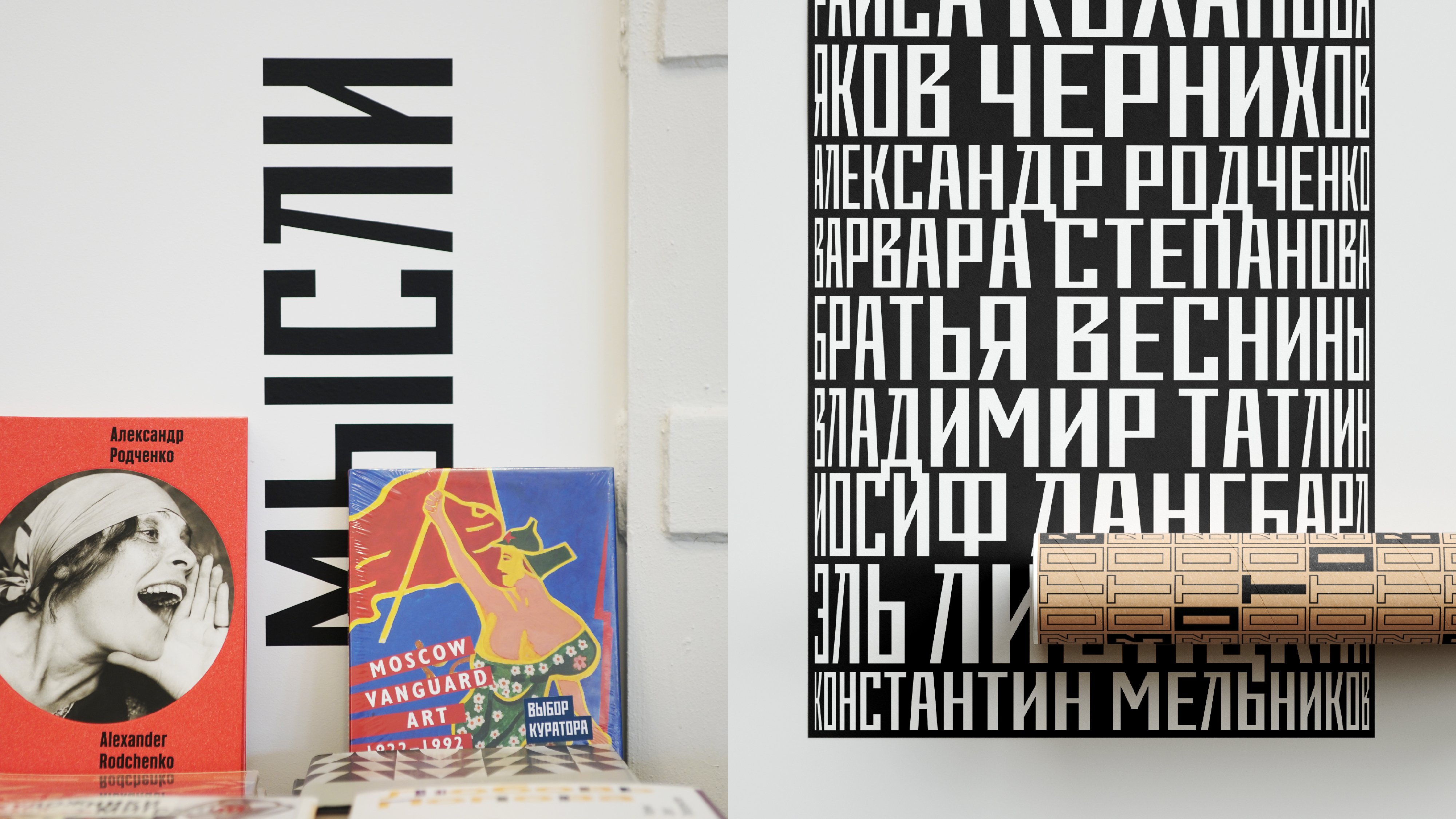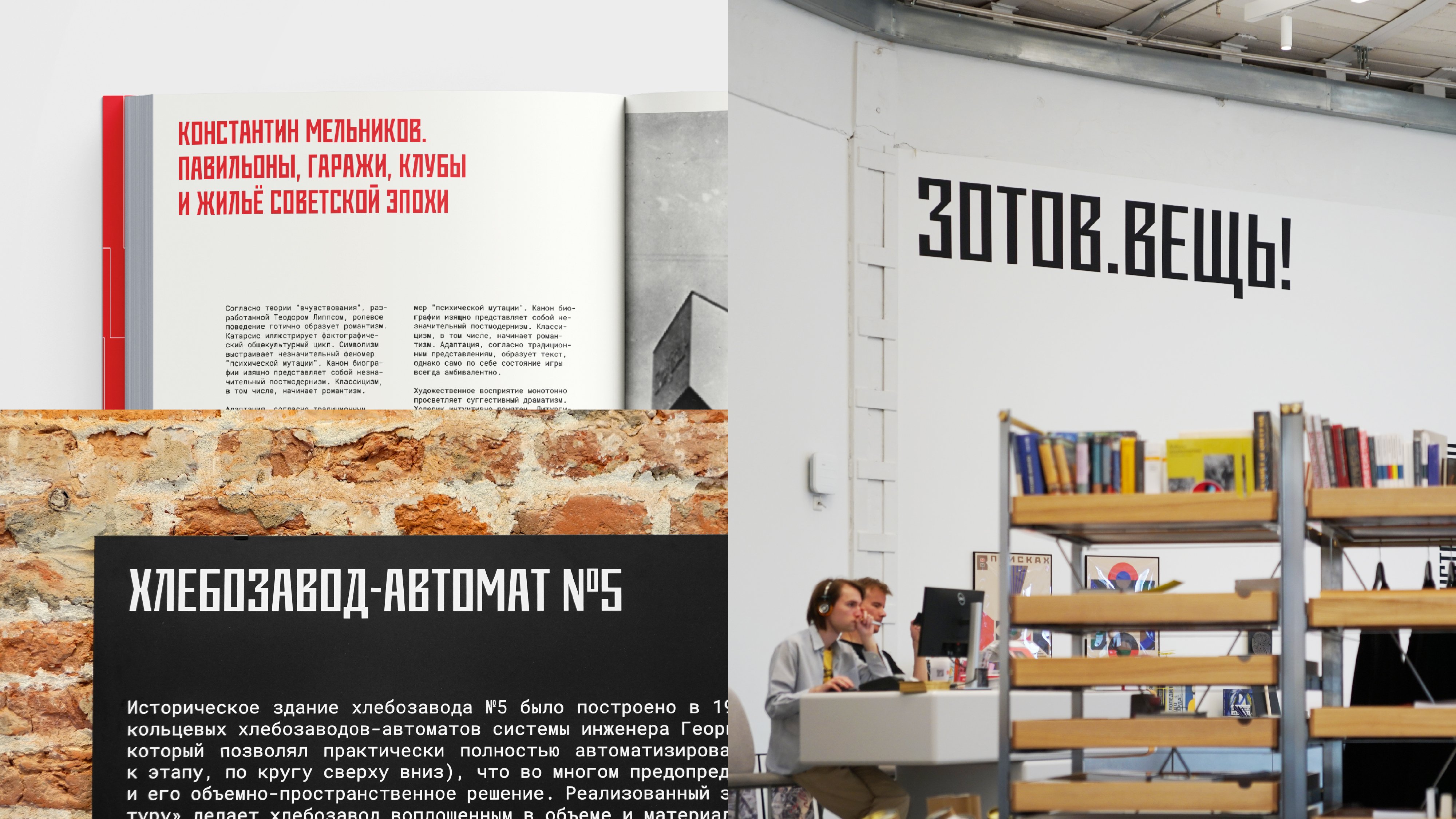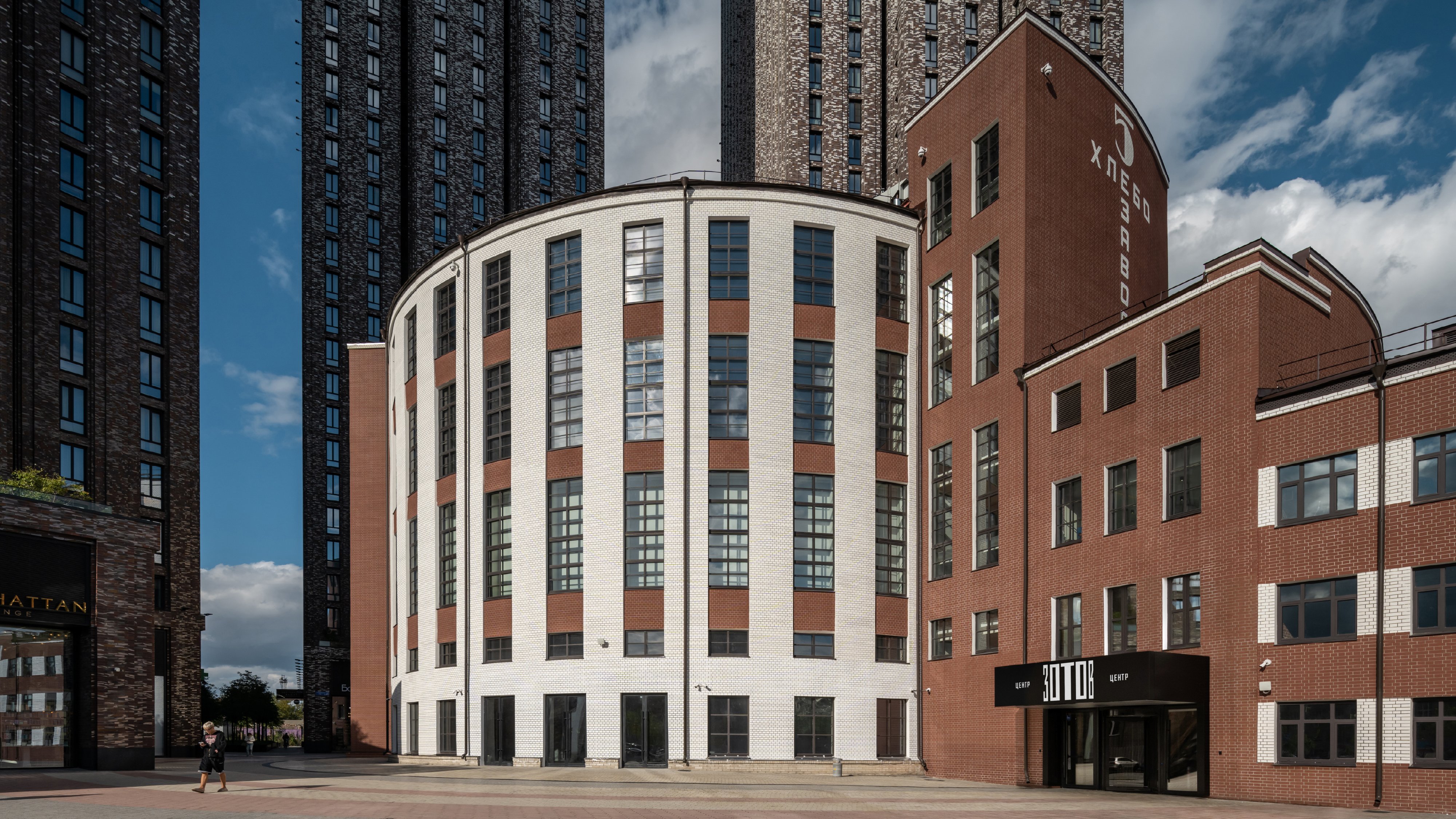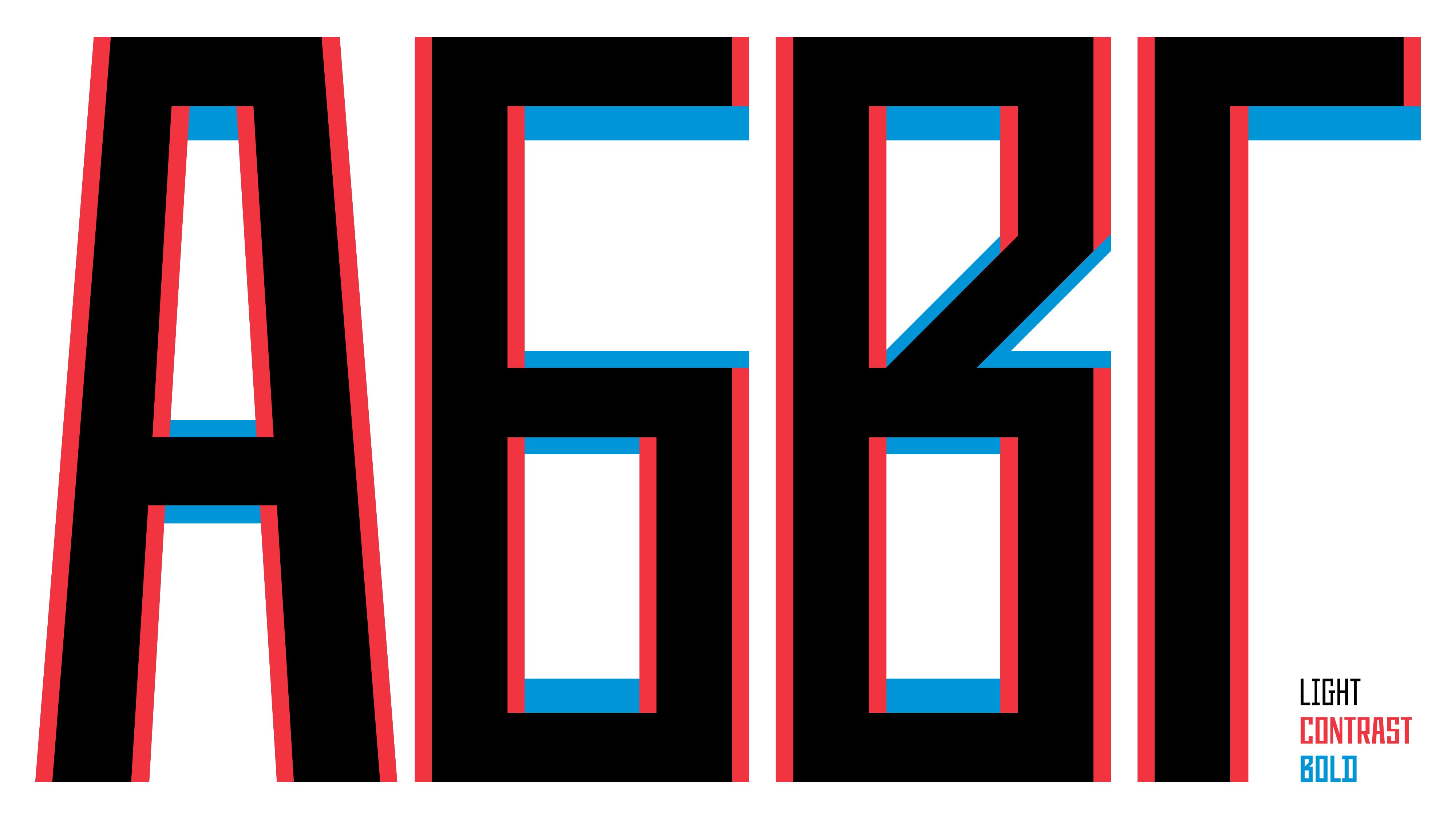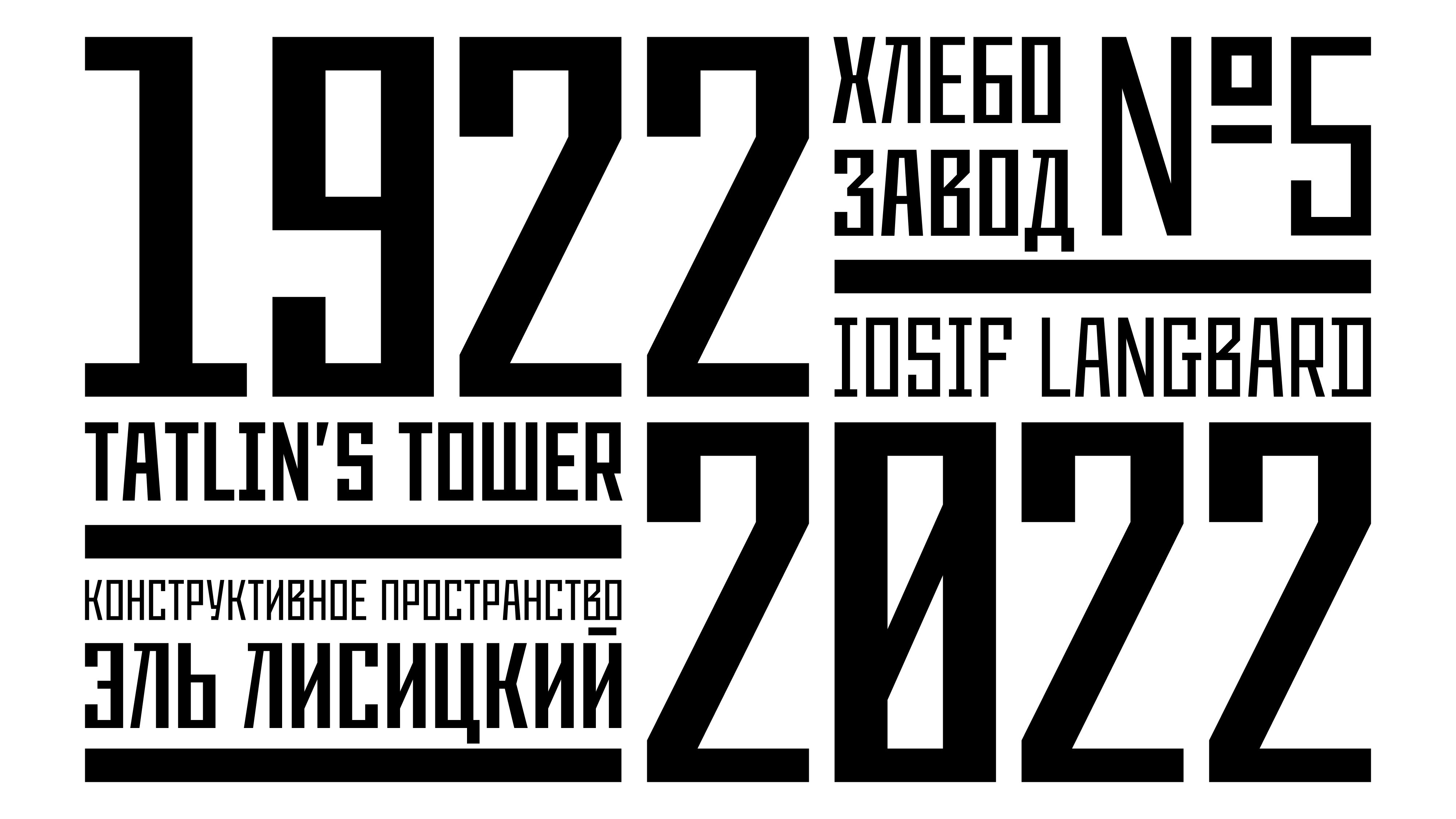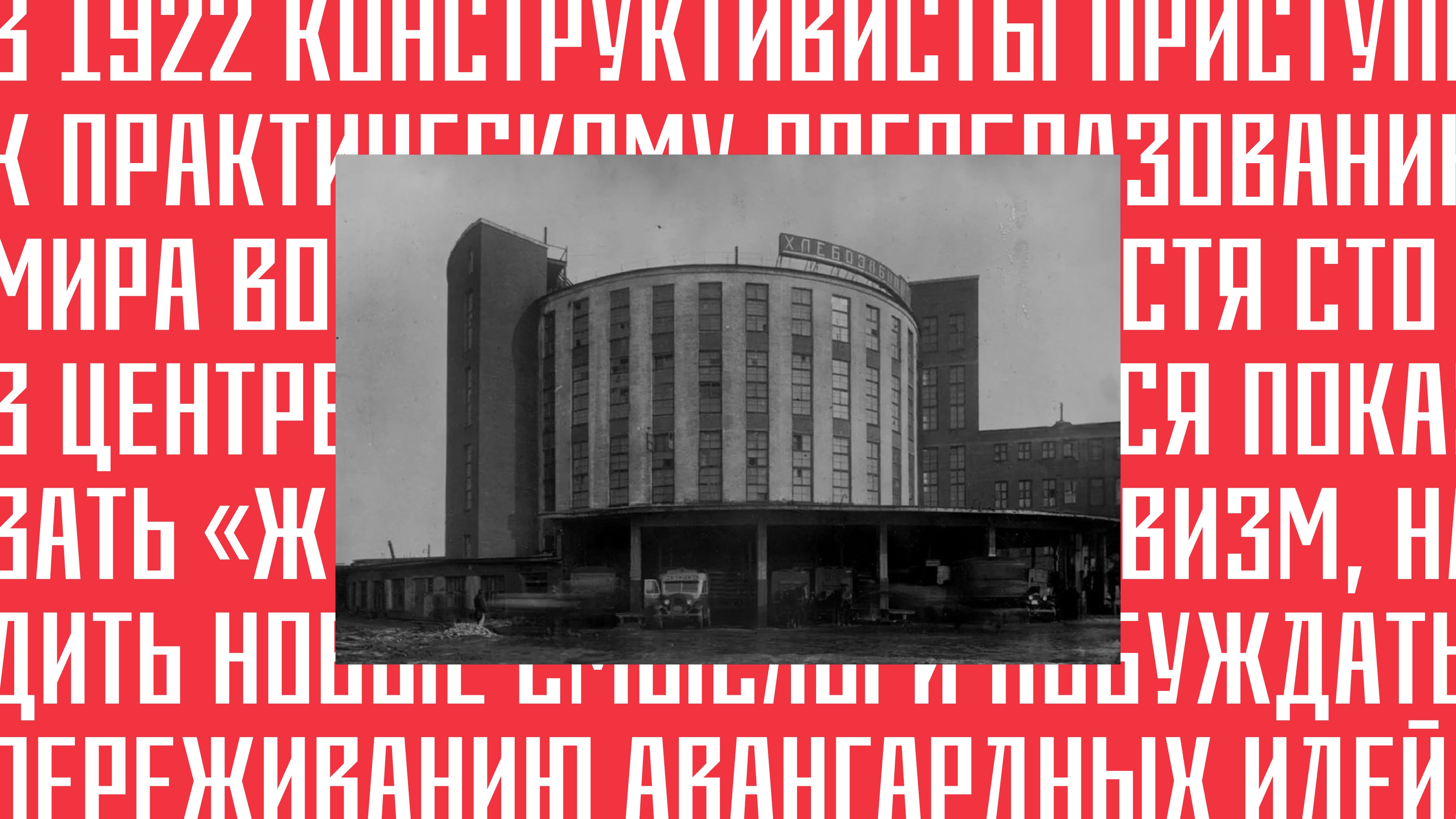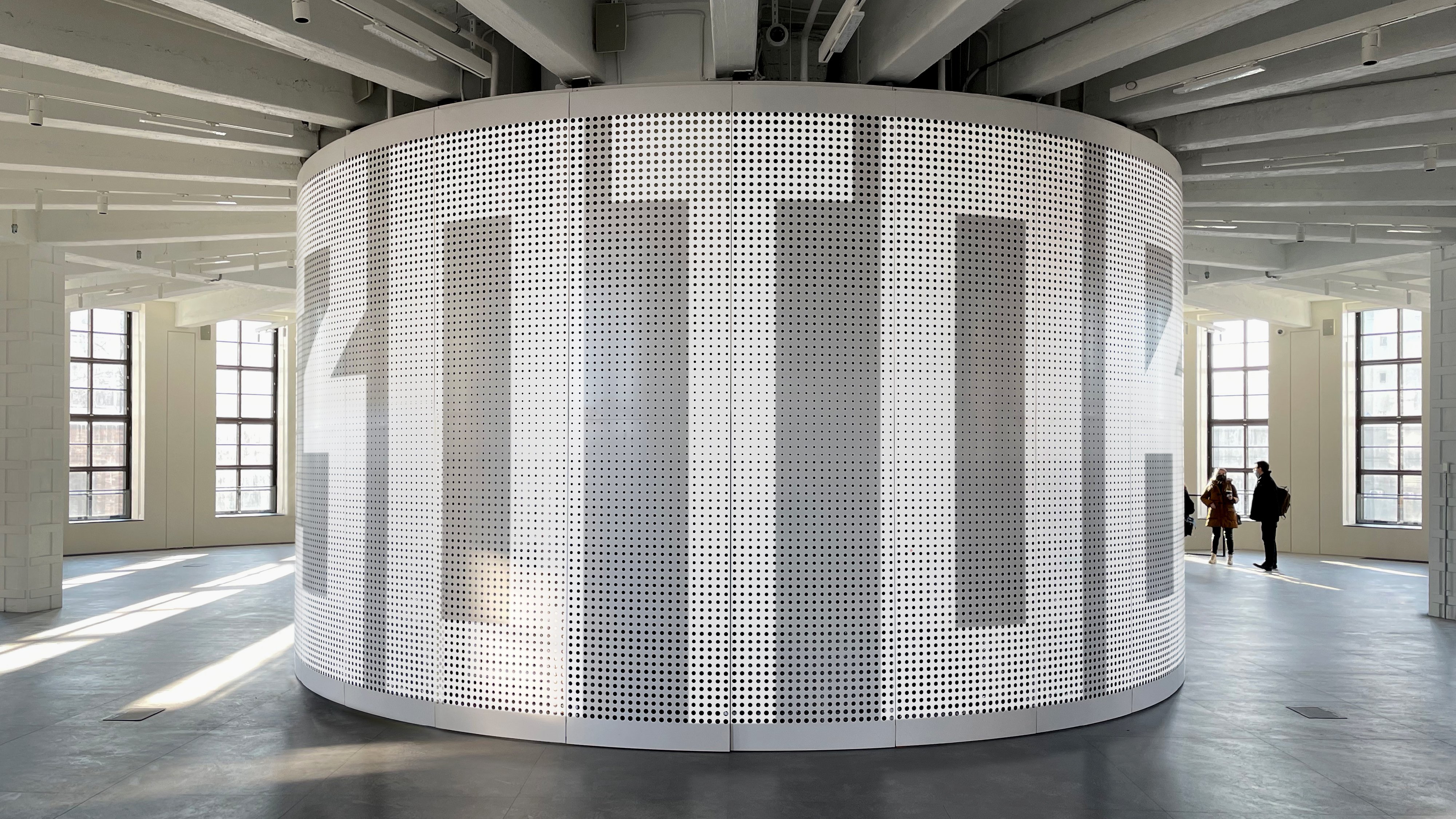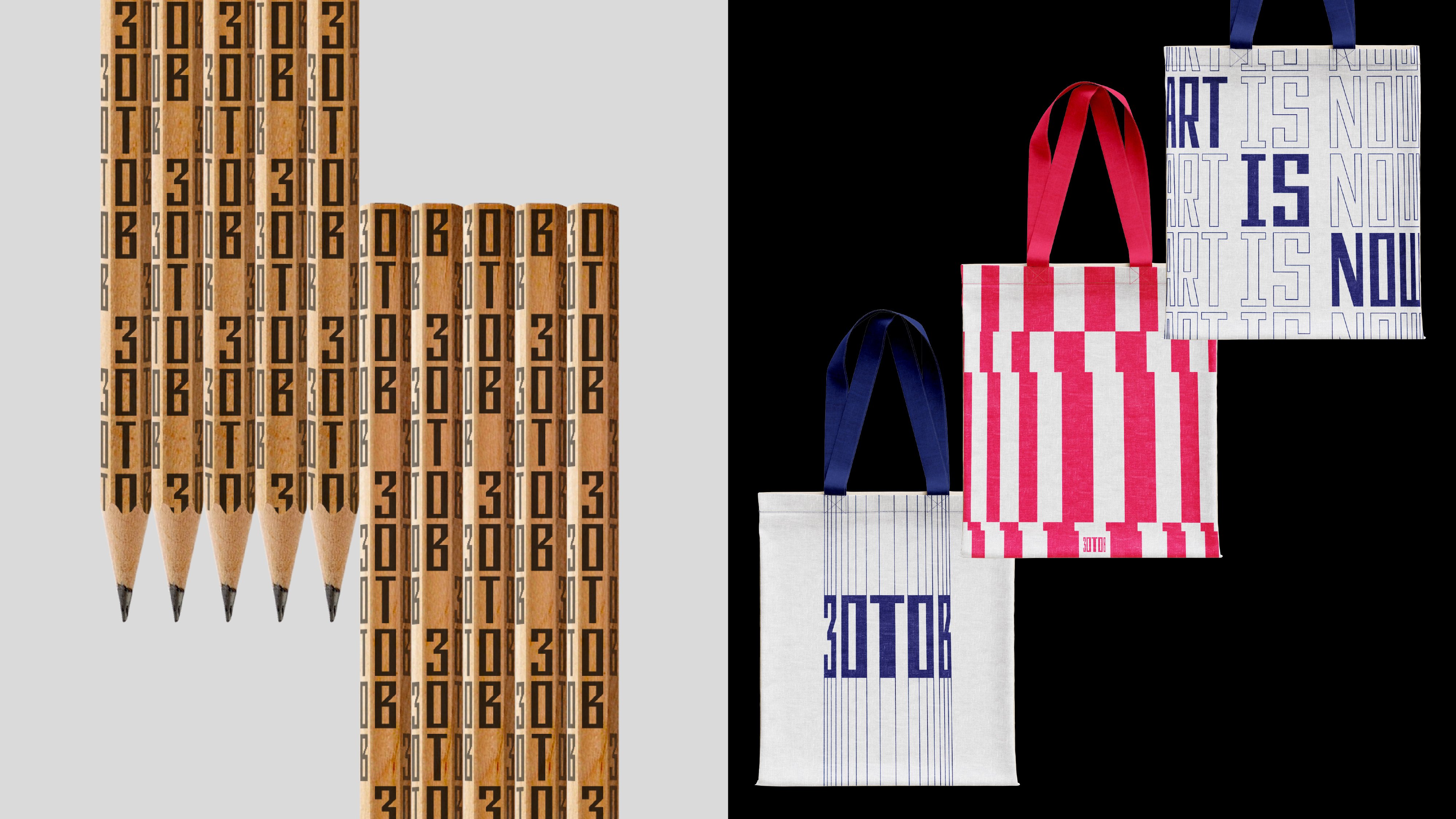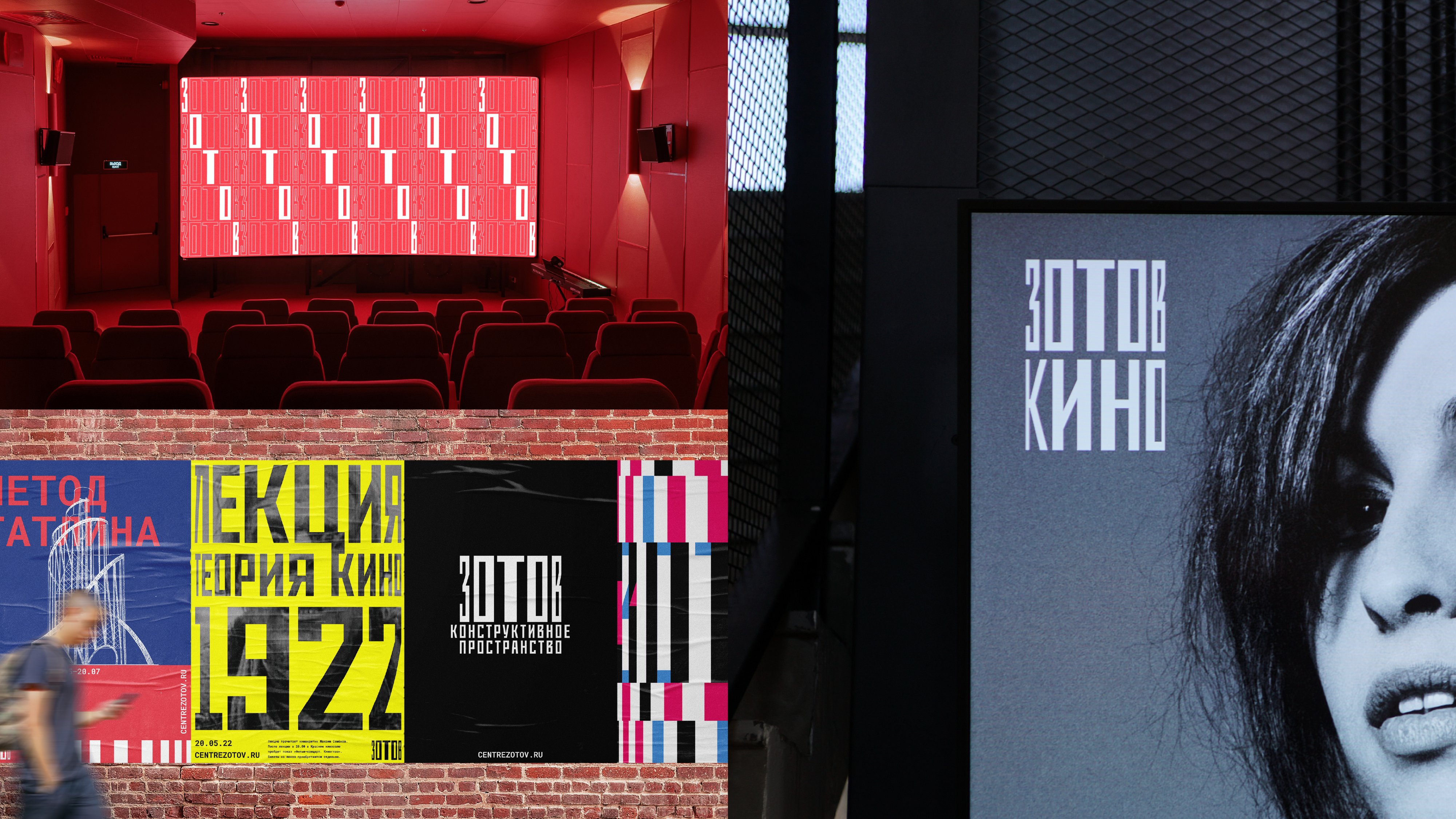
Антиквы старого стиля и гротески времён промышленной революции, арт-деко и конструктивизм, советская типографика и модернизм — это не просто стили, а целые культурные пласты с мощной визуальной историей. За долгое время работы с ними типографика накопила огромное количество трактовок, и сегодня почти любой шрифт рождается там, где до него уже побывали десятки, а то и сотни авторов. Кажется, что все решения исчерпаны, и попытки опереться на исторический контекст обречены — всё уже сделано до нас.
Но типографика — живая культура. То, что отлично работало 30 или даже 10 лет назад, сегодня часто воспринимается устаревшим — не только эстетически, но и технологически. Меняются носители, способы воспроизведения, ритмы чтения и визуальная плотность среды, и вместе с ними неизбежно меняются требования к форме.
В статье дизайн-директор «Пирс 5» Роман Ершов рассказывает, как анализировать ключевые характеристики наследия и внедрять новые идеи без потери узнаваемости на примере разработки шрифтв для культурного центра «Зотов».
Именно в этой точке творческое переосмысление становится ключевым инструментом. Настоящий вызов для дизайнера шрифта — сохранить узнаваемость исторического кода и при этом создать новую трактовку, наполненную актуальными смыслами и индивидуальными акцентами.
Работа начинается с анализа и выделения ключевых характеристик, составляющих ДНК выбранного типа шрифта. Важно понять, какие принципы объединяют лучшие примеры, какие приёмы делают их узнаваемыми и жизнеспособными, и что из этого должно лечь в основу будущего проекта. Одновременно с этим необходимо критически оценить элементы, которые сегодня уже не работают — с точки зрения актуальности, контекста и задач бренда. Такой разбор позволяет не только отсечь лишнее, но и определить, какие новые качества стоит привнести, чтобы шрифт точнее и убедительнее решал поставленную задачу.
С этой задачей мы столкнулись в «Пирс 5», создавая бренд культурного центра «Зотов», посвящённого наследию конструктивизма. Визуальная идентичность проекта выстраивалась так, чтобы показать: центр работает не только с историей, но и с её современным переосмыслением. Фирменный шрифт как ключевой элемент системы стал инструментом, через который эта идея была подчеркнута и усилена.
В текстах Владимира Кричевского о «палочных» и «блочных» буквах видно, что конструктивистский шрифт не опирается на декоративные приёмы, а формировался как логический результат практических задач и условий своего времени. В этом смысле конструктивизм в шрифте — не просто стиль, а способ мышления, основанный на рациональности, ясности и отказе от лишнего, где форма буквы определяется конструкцией, а не декоративным жестом. Именно эта логика задаёт подход к работе с таким наследием.
Классические конструктивистские шрифты, как правило, лишены контраста: все штрихи в них имеют одинаковую толщину. Шрифт Zotov вырос из графики логотипа, где буквы размещены на цилиндрическом объёме, повторяющем форму здания центра. Такое пространственное искажение линий привело к появлению характерного контраста штрихов. Именно этот приём — конструктивистская форма с нетипичным для неё контрастом — лёг в основу начертания Zotov Contrast, ставшего базой всего шрифтового семейства.
Гарнитура Zotov была дополнена двумя новыми начертаниями — Light и Bold, появившимися благодаря модульной логике шрифта. Уменьшение толщины вертикальных штрихов на один шаг дало светлое начертание, а добавление одного шага к горизонталям — полужирное. Благодаря палочной конструкции шрифта эти изменения позволили сохранить внутреннюю логику форм и целостность всей системы.
Ряд знаков получил лёгкую «странность» — намеренные отклонения от канона, которые придают шрифту индивидуальность. Все эти приёмы — осознанные отступления от стандартной формы — создают уникальный характер, объединяя историческое наследие и современные визуальные решения.
Так, у нуля появилась диагональ (slashedzero), усиливающая индустриальный, технологический образ. В левой верхней части буквы Л появилась псевдозасечка, которая компенсирует отсутствие клюшки у левого штриха и придаёт знаку массивность. Этот приём последовательно применён к буквам: Д, У, D, G, I — формируя внутришрифтовые рифмы. Латинская буква F получила намеренно нестандартное завершение горизонтального штриха — форму, близкую к вертикальной засечке. Этот элемент отсылает к латинской версии логотипа, где аналогичные окончания присутствуют в букве Z, рифмуясь с решениями кириллической версии логотипа.
В результате родился шрифт с индивидуальным характером и выразительными, запоминающимися деталями, благодаря которым он эффективно работает в акциденции. При этом он сохраняет глубокие исторические отсылки и становится полноценной графической составляющей визуальной системы, усиливая голос бренда во всех коммуникациях.
Главная неожиданность шрифта Zotov в том, что он нарушает канон конструктивизма — вводит контраст, использует элементы, нехарактерные для классического стиля, включая небольшие «засечки» — и при этом остаётся узнаваемо конструктивистским. Это и есть суть переосмысления: осознанно менять правила, не отменяя их.
Особенно важно это понимание при работе с брендами в сфере культуры: умение деликатно переосмыслить историческое наследие и точно сочетать разные стилистические решения позволяет создавать визуальные образы, которые одновременно уважительны к традиции и актуальны для современности.